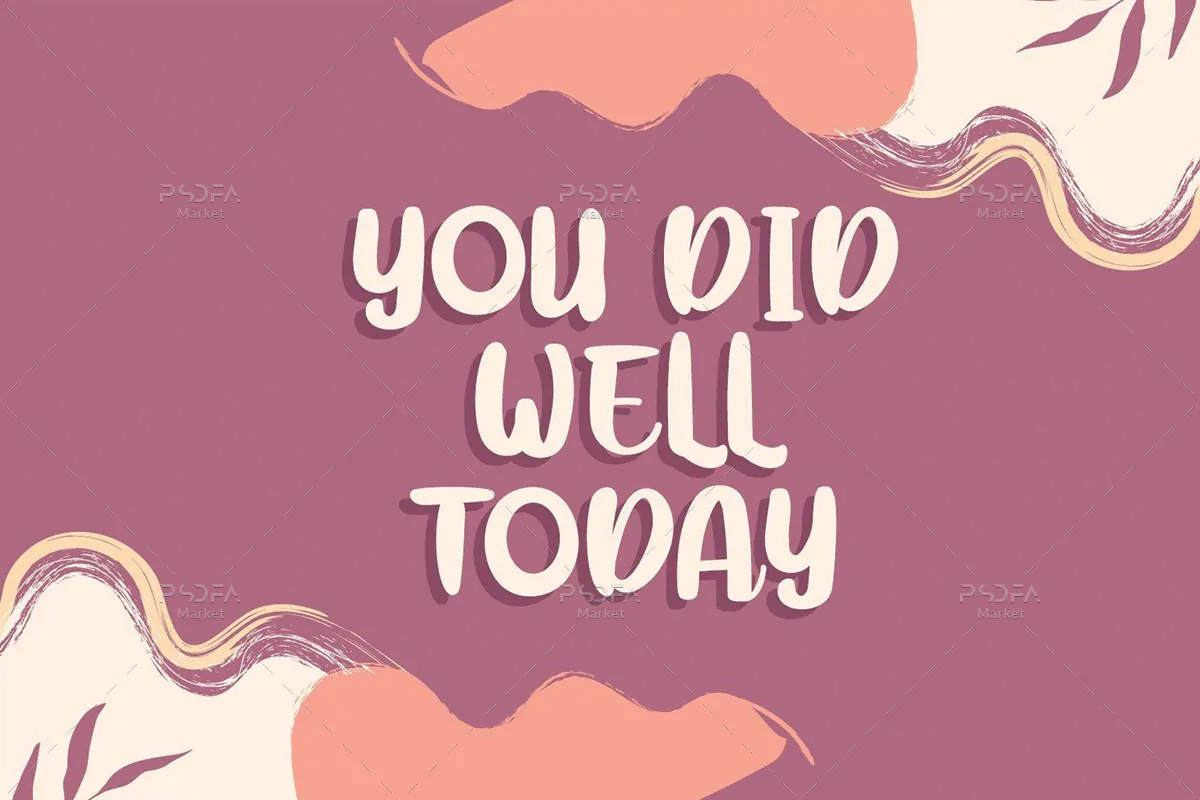
فونت دستنویس و سرهم
فونت دستنویس و سرهم Mikela یک قلم انگلیسی فوق العاده زیبا است که مناسب جهت استفاده در طرح و پروژههای گرافیکی مختلف میباشد. فونت Mikela با وزن معمولی طراحی شده است که میتوان از آن در طراحی انواع پوستر، کارت تبریک، بنر، بسته بندی محصولات، آرایشی و بهداشتی، لوازم التحریر و … استفاده نمود.